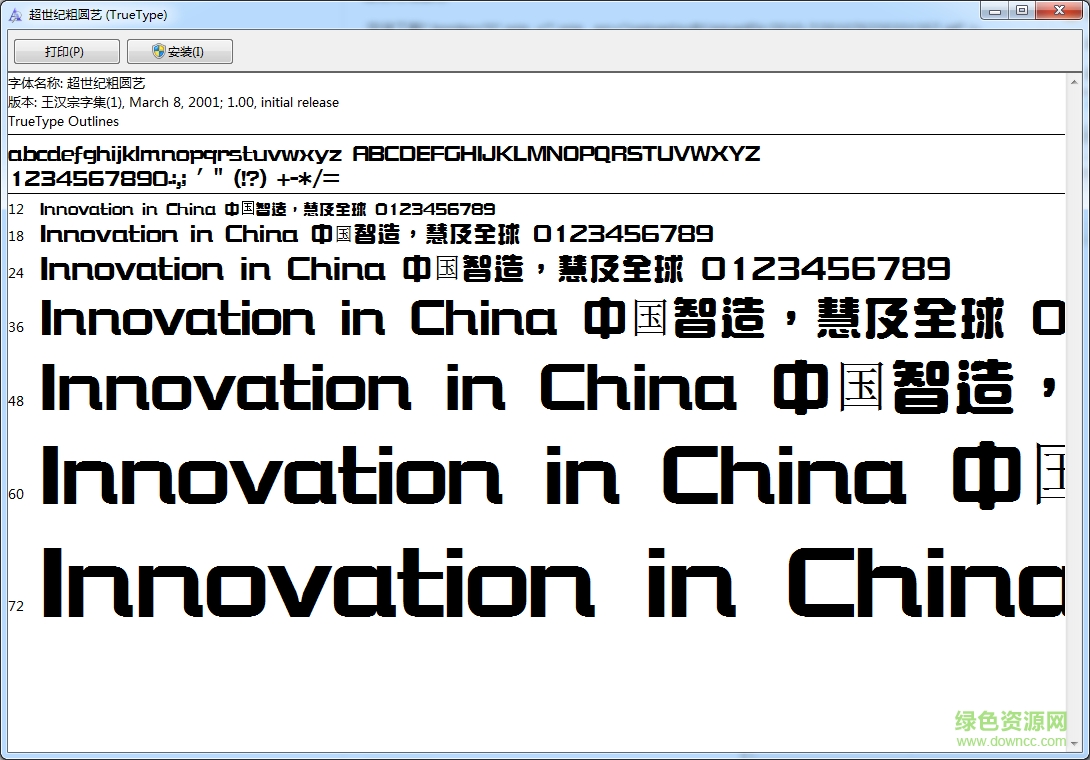
超世紀(jì)粗圓藝是一款比較圓潤的超世紀(jì)字體軟件,字體粗細(xì)顯示對稱,線條感十足,而且字體在美工設(shè)計(jì)方面是非常不錯的,字體打印出來也很棒,一鍵安裝免費(fèi)使用非常便捷??靵砭G色資源網(wǎng)下載體驗(yàn)吧!
超世紀(jì)粗圓藝是超世紀(jì)字體庫中一種字體,常用于美工設(shè)計(jì)方面,喜歡的朋友不要錯過。
審美要的高雅很多。在海報(bào)與網(wǎng)站圖標(biāo)中運(yùn)用比較多,不適合做正文和標(biāo)題的選擇,比較適合副標(biāo)題文字的選擇。